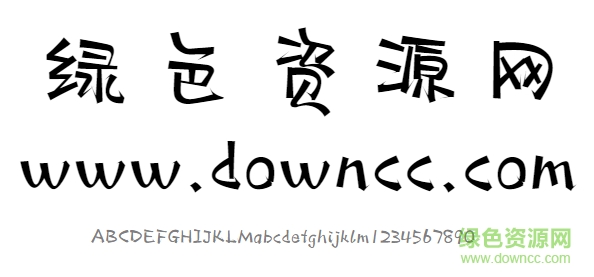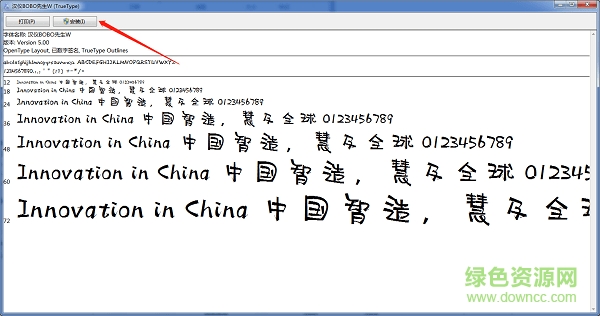
漢儀bobo先生字體是漢儀發(fā)布的新字體,以搞怪都市為題材,奇特的字體畫風(fēng),無論是字體的排版還是作為單個(gè)醒目的標(biāo)題,都能為你呈現(xiàn)出不同的視覺效果,所以這款字體用途多樣,喜歡就來綠色資源網(wǎng),還有更多的精彩等著你哦!
漢儀bobo先生字體支持多種不同文字的顯示,同時(shí)還有超多的標(biāo)點(diǎn)也做了特別的設(shè)計(jì),能夠方便喜歡此款字體的用戶使用到多個(gè)不同的場景,書寫出你的風(fēng)格!